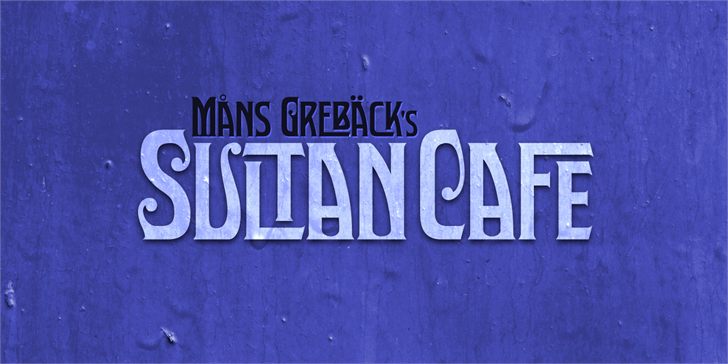
A fonte Sultan Cafe é uma elegante serif que se encaixa perfeitamente para criações com toques sofisticados. Suas linhas rígidas e detalhes finos conferem ao seu design um ar de seriedade, mas também uma delicadeza que o torna adequado tanto para textos formais quanto para trabalhos mais pessoais ou artísticos. Inspirada pelo estilo clássico dos cafés do século XX, essa fonte foi projetada por Hamilton e carrega consigo a essência de um ambiente acolhedor e respeitável. Seja para criar logotipos memoráveis, design gráfico sofisticado ou até mesmo capas de livros de receitas, Sultan Cafe traz um toque que combina perfeitamente com uma experiência café cuidadosamente elaborada. A fonte apresenta uma variedade de opções, incluindo diferentes tamanhos e graus de boldness, permitindo-a ser usada de diversas maneiras – seja para criar textos grandes e imponentes ou pequenos detalhes delicados. Ela é perfeita para aqueles que buscam um design elegante que destaca a sofisticação do café, uma fonte ideal para designers gráficos em busca de opções originais e versáteis. Visite o site oficial da MansGreback.com/sultan-cafe para explorar as possibilidades criativas desta fonte única.